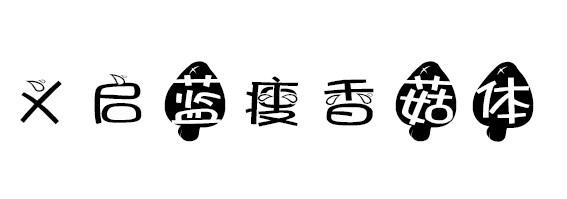
义启蓝廋香菇体,字体样式是一款十分可爱的字体,由网络搜索热词 “蓝廋香菇 ”引伸而成的一款创意字体 ,依据字型参差含有小蘑菇印痕 ,总体字型 圆扁稚嫩,构造上伸缩张弛有度 ,所向披靡 ,总体上实际效果十分优异 。适用于PS字体设计,海报设计等。
字体简介:义启蓝瘦香菇体,灵感来自于广西南宁一小哥失恋后录的一段视频:蓝瘦,香菇,本来今颠高高兴兴,泥为什莫要说这种话?蓝瘦,香菇在这里。第一翅为一个女孩屎这么香菇,蓝瘦。泥为什莫要说射种话,丢我一个人在这里。